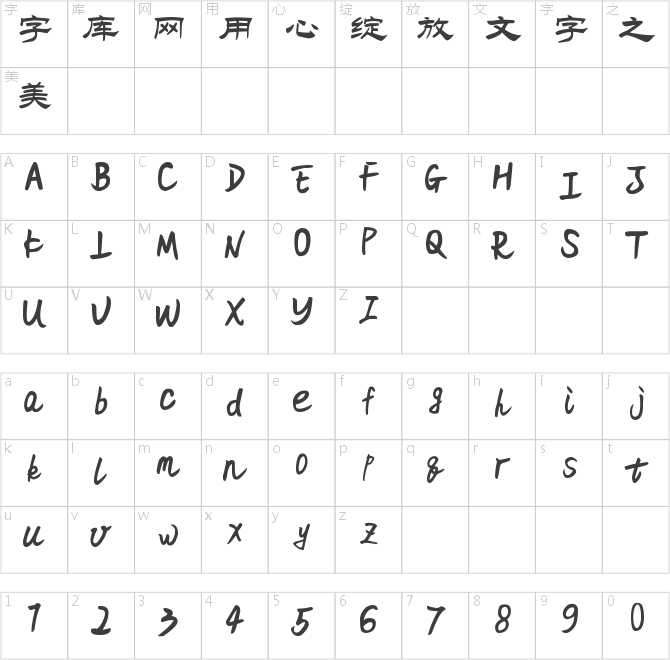
爨體字所具有的古韻、渾厚、拙樸特質(zhì),與客家文化相互交融。
由此碰撞出專屬于客家人的鼎獵客家體。鼎獵客家體(作品登記證書登記號(hào):陜作登字-2024-F-00013784),是一套根據(jù)簡(jiǎn)體中文漢字編碼國家標(biāo)準(zhǔn)(GB2312編碼)設(shè)計(jì)的字體,并在此基礎(chǔ)上一共設(shè)計(jì)了6789個(gè)簡(jiǎn)體漢字。
鼎獵客家體為一款原創(chuàng)字體,具有其獨(dú)特的字形風(fēng)格,適用于廣告、書籍、海報(bào)等多個(gè)場(chǎng)合。其中,特別增加了客家話專屬漢字?jǐn)?shù)十個(gè)。